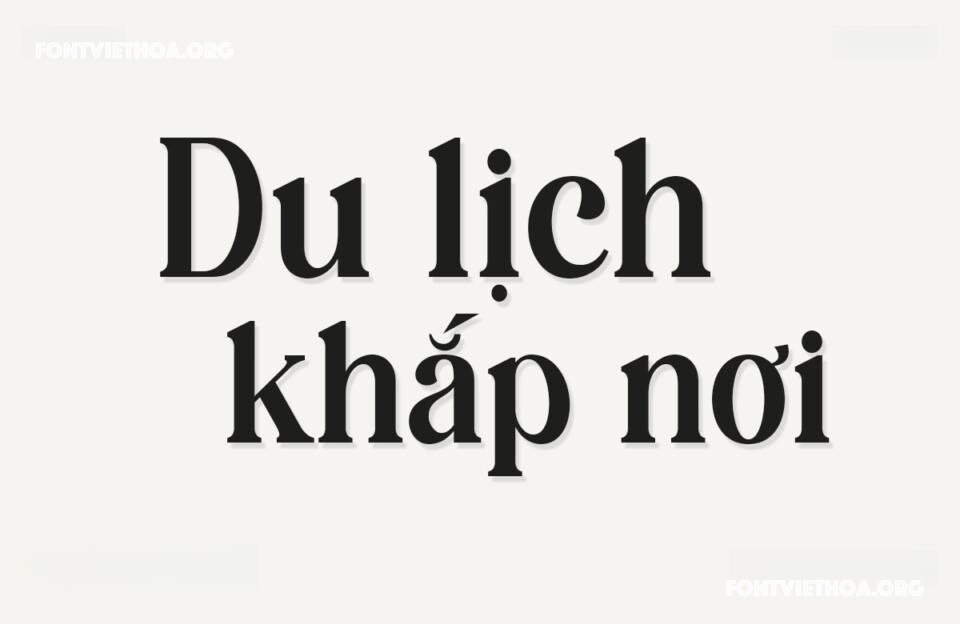
Tên font: Font Việt hóa VIP Bugalo
Tác giả: HansCo
Font Việt hóa VIP Bugalo là một font có chân, nét to vừa phải, phù hợp với các thiết kế tiêu đề, thời trang, tạp chí. Với kiểu dáng đẹp mắt và hiện đại, font này đã trở thành lựa chọn của nhiều nhà thiết kế. Trong bài viết này, chúng tôi sẽ giới thiệu về font Việt hóa VIP Bugalo và cách sử dụng nó trong thiết kế.
Font Việt hóa VIP Bugalo có nhiều lợi ích khi sử dụng trong thiết kế. Đầu tiên, nó giúp tạo ra các tiêu đề đẹp mắt và hiện đại, thu hút sự chú ý của người xem. Thứ hai, nó phù hợp với nhiều phong cách thiết kế khác nhau, từ thời trang đến tạp chí.